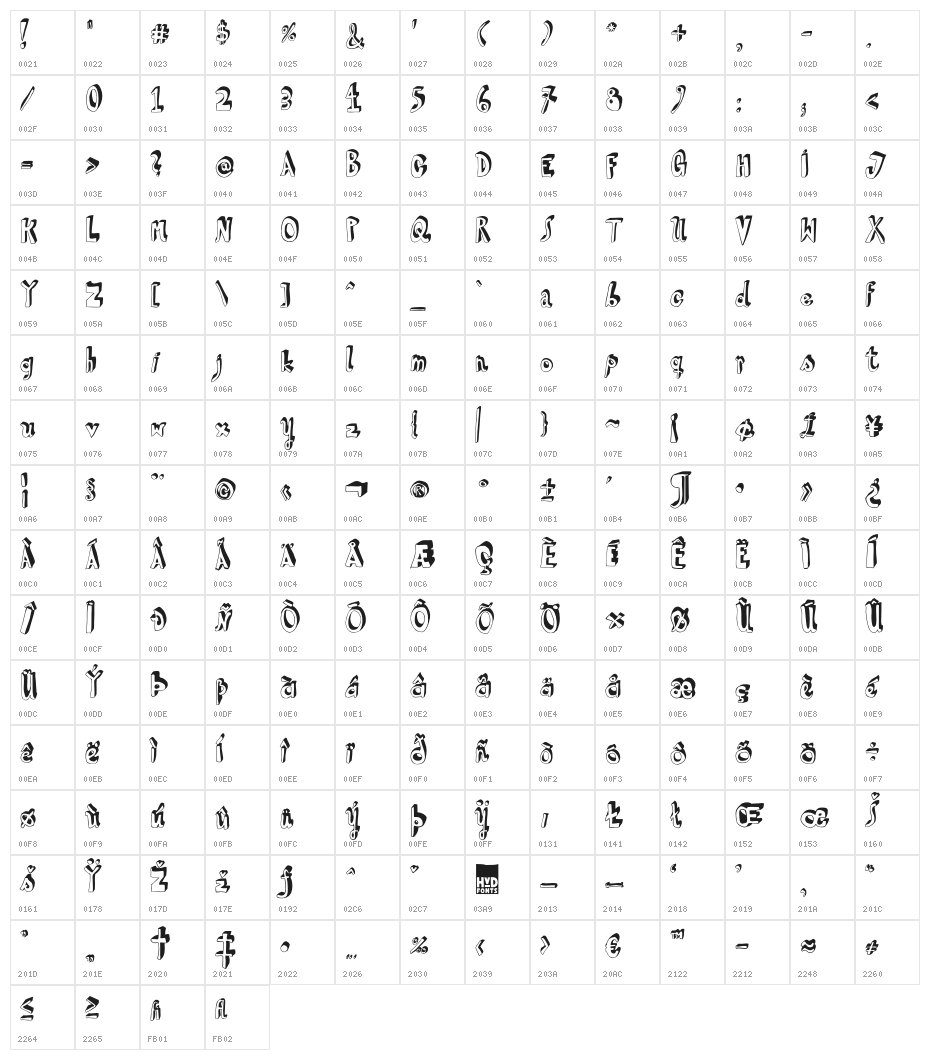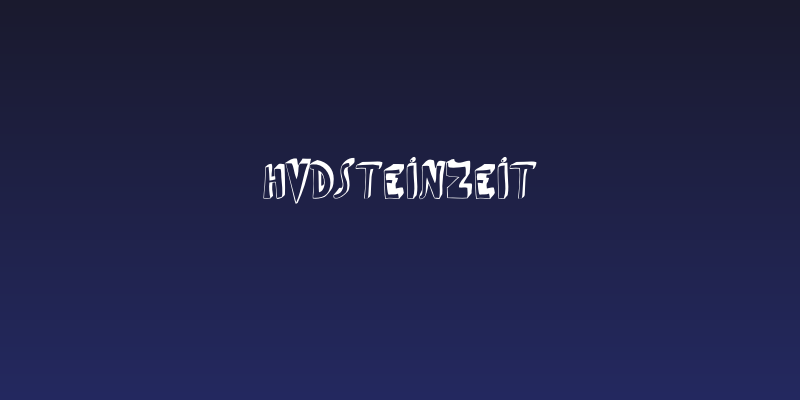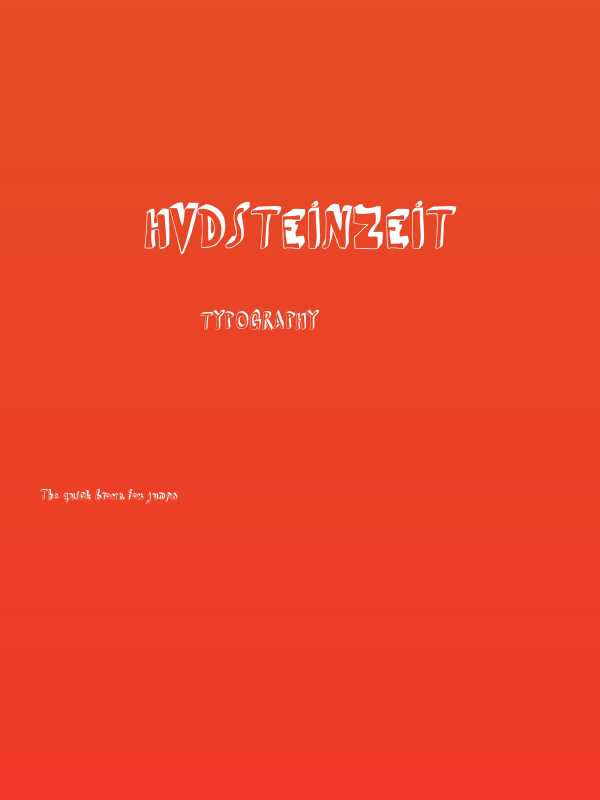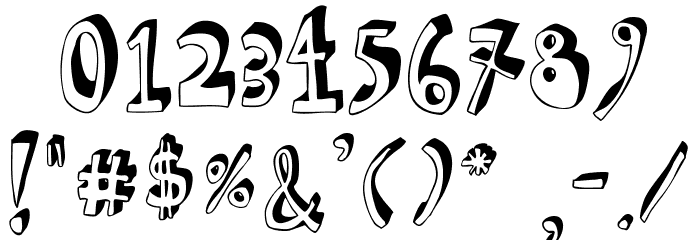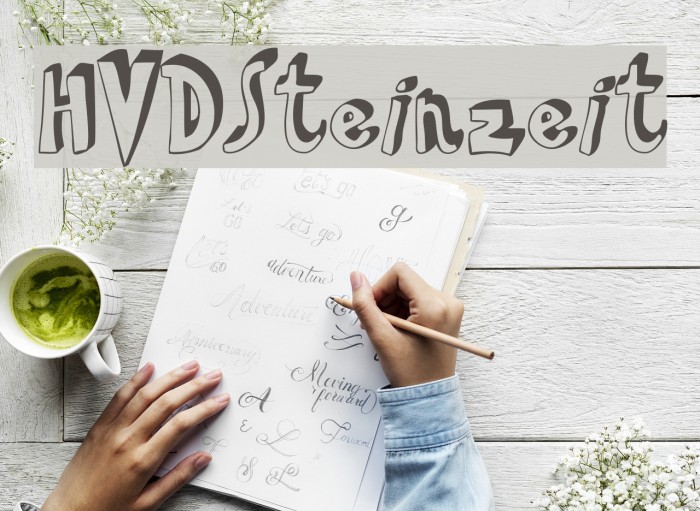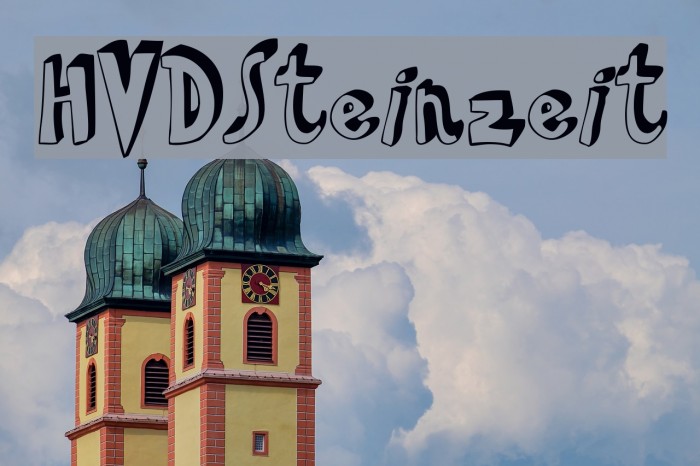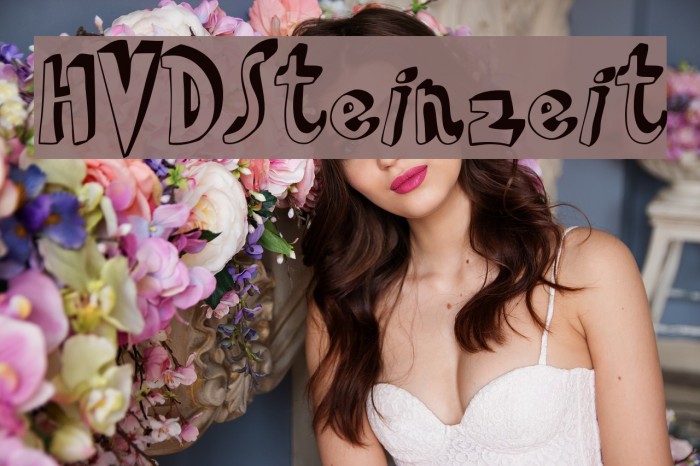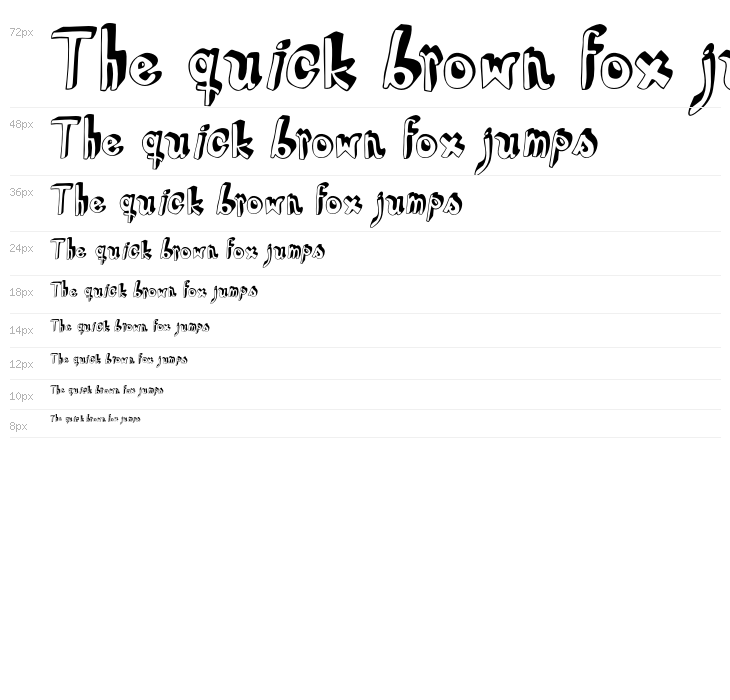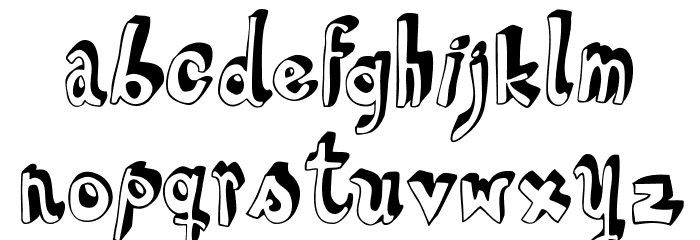
HVDSteinzeit Font
| Stile generale | Playful, Cartoonish |
| Caso d'uso | Headlines, Posters, Branding |
| Progetti proposti | Ideal for children's books, comic strips, playful branding, and creative posters. |